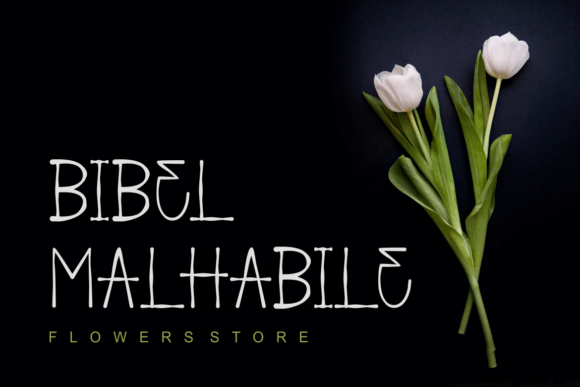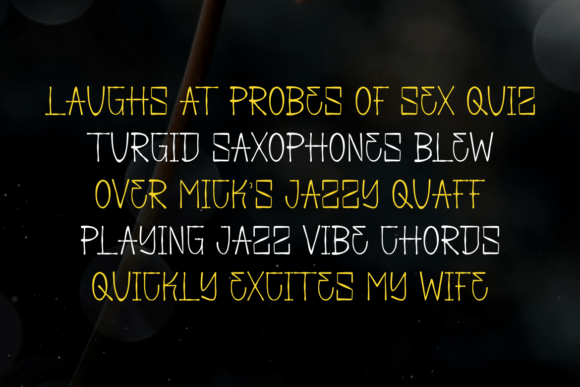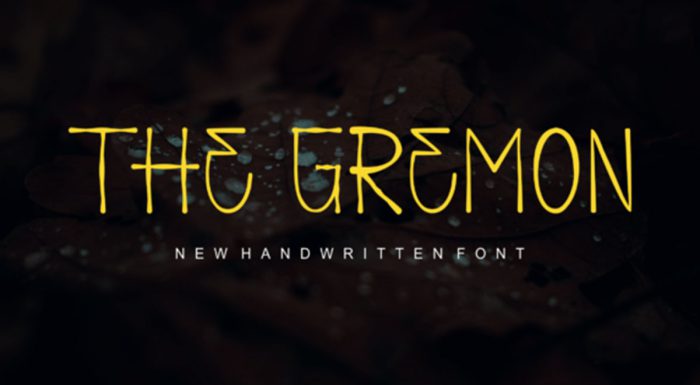
فونت The Gremon انگلیسی
| ⭐ توضیحات | معرفی محصول جدید ** قلم گرمون** – فونت مدرن
** فونت Gremon ** – فونت مدرن یک فونت نمایشگر برجسته و معتبر است. این فونت برای هر پروژه برندسازی مانند لوگو، esport و بسیاری موارد دیگر مناسب است. برجسته در طیف گسترده ای از زمینه ها. |